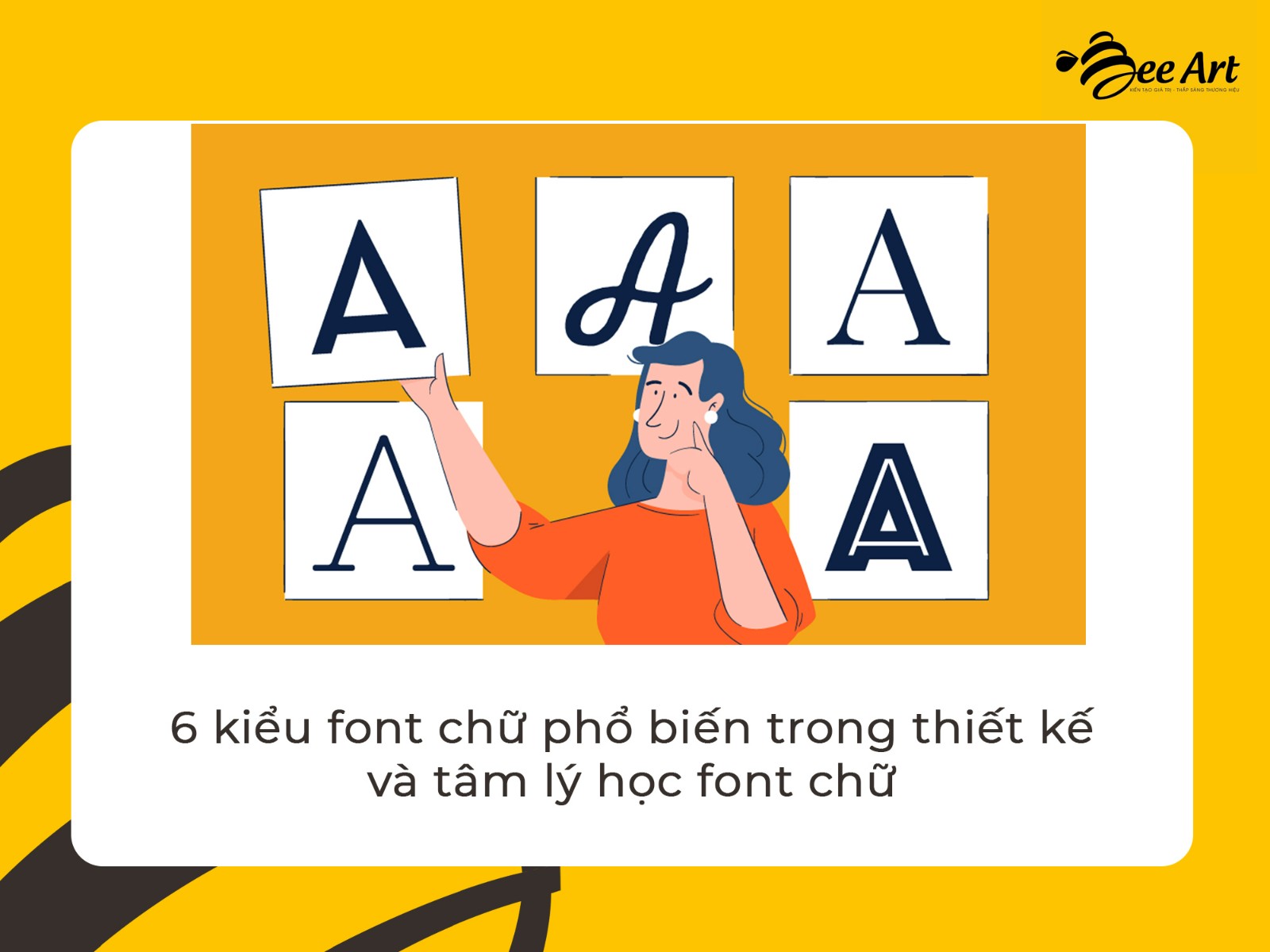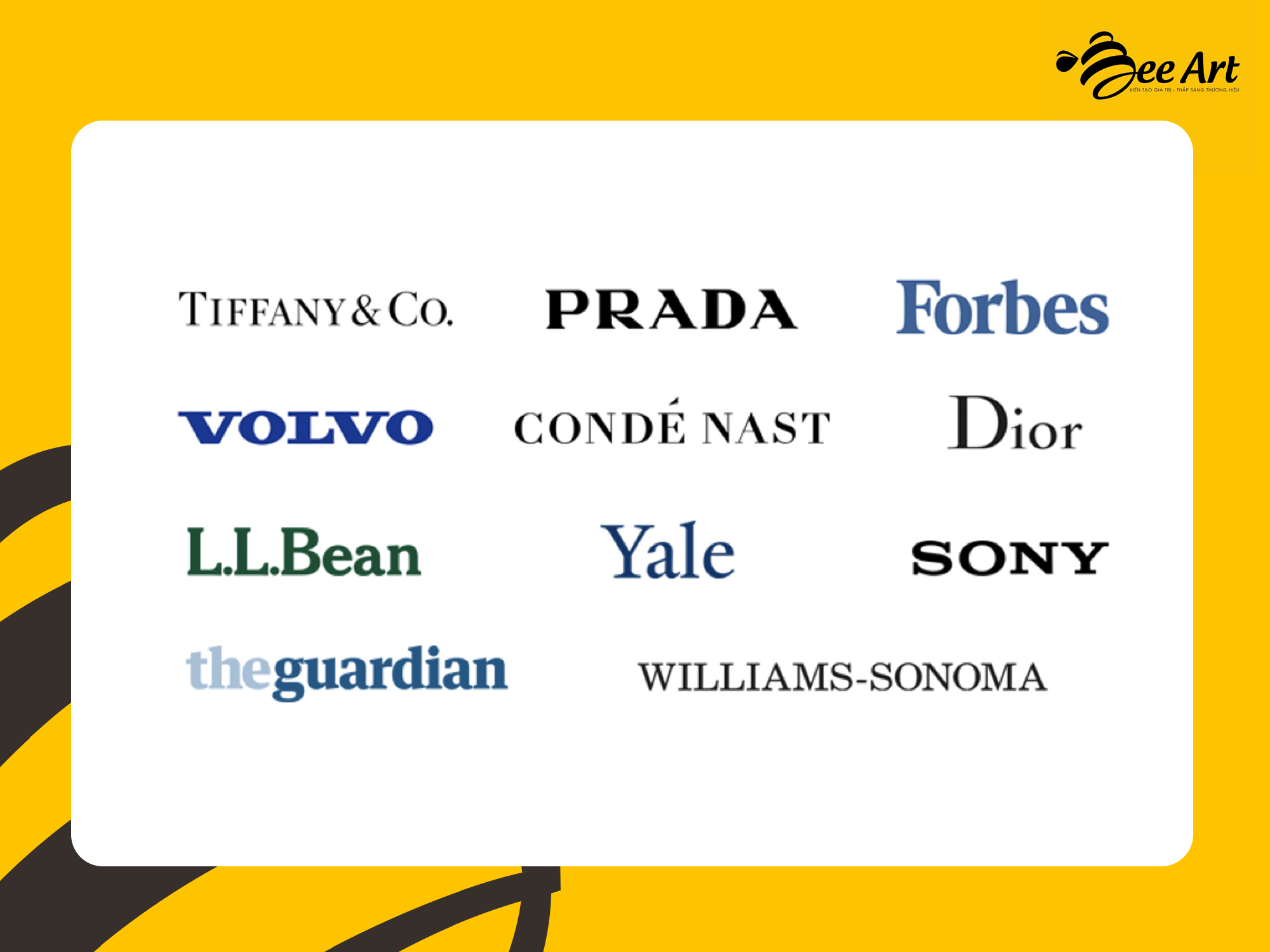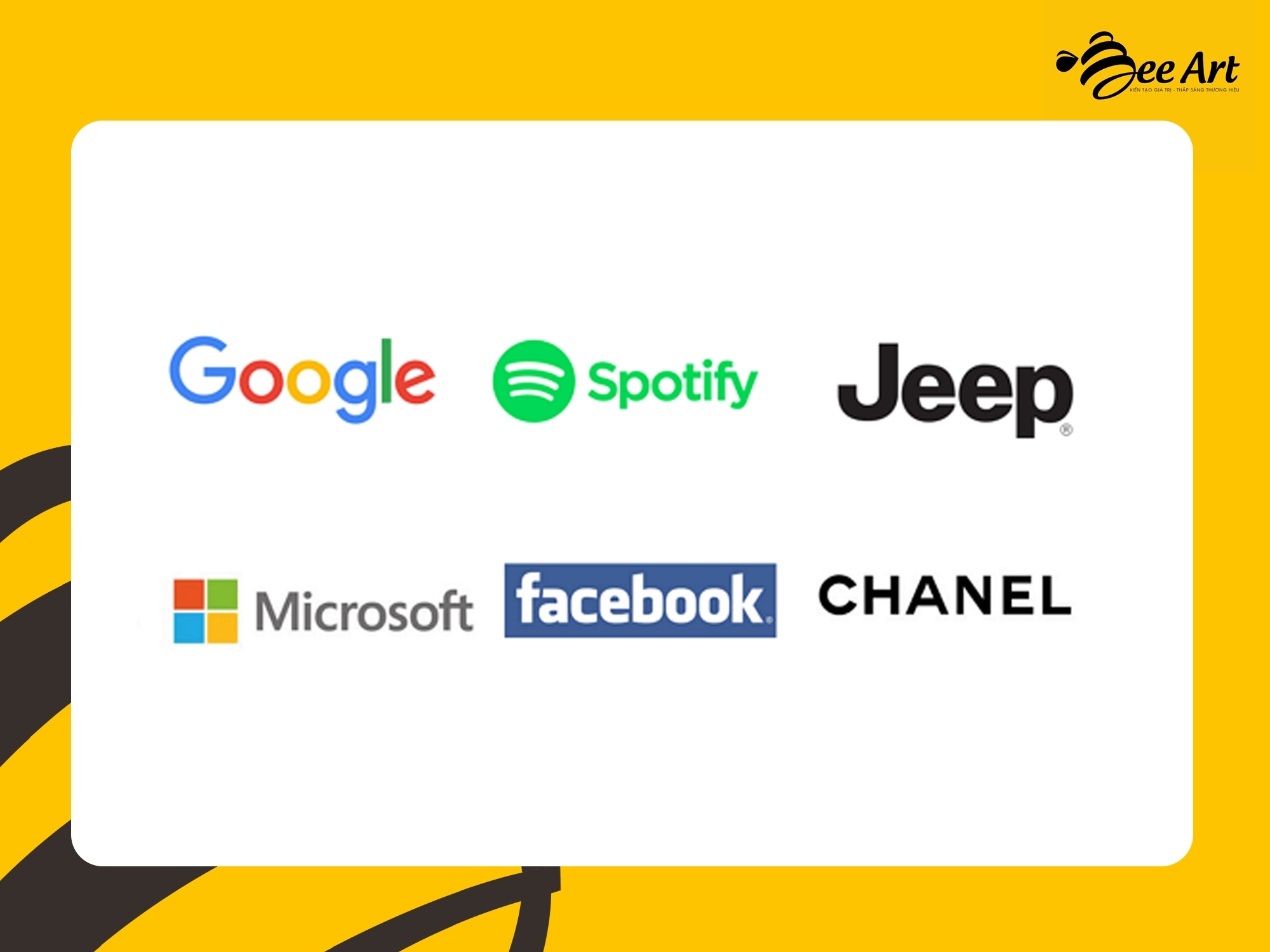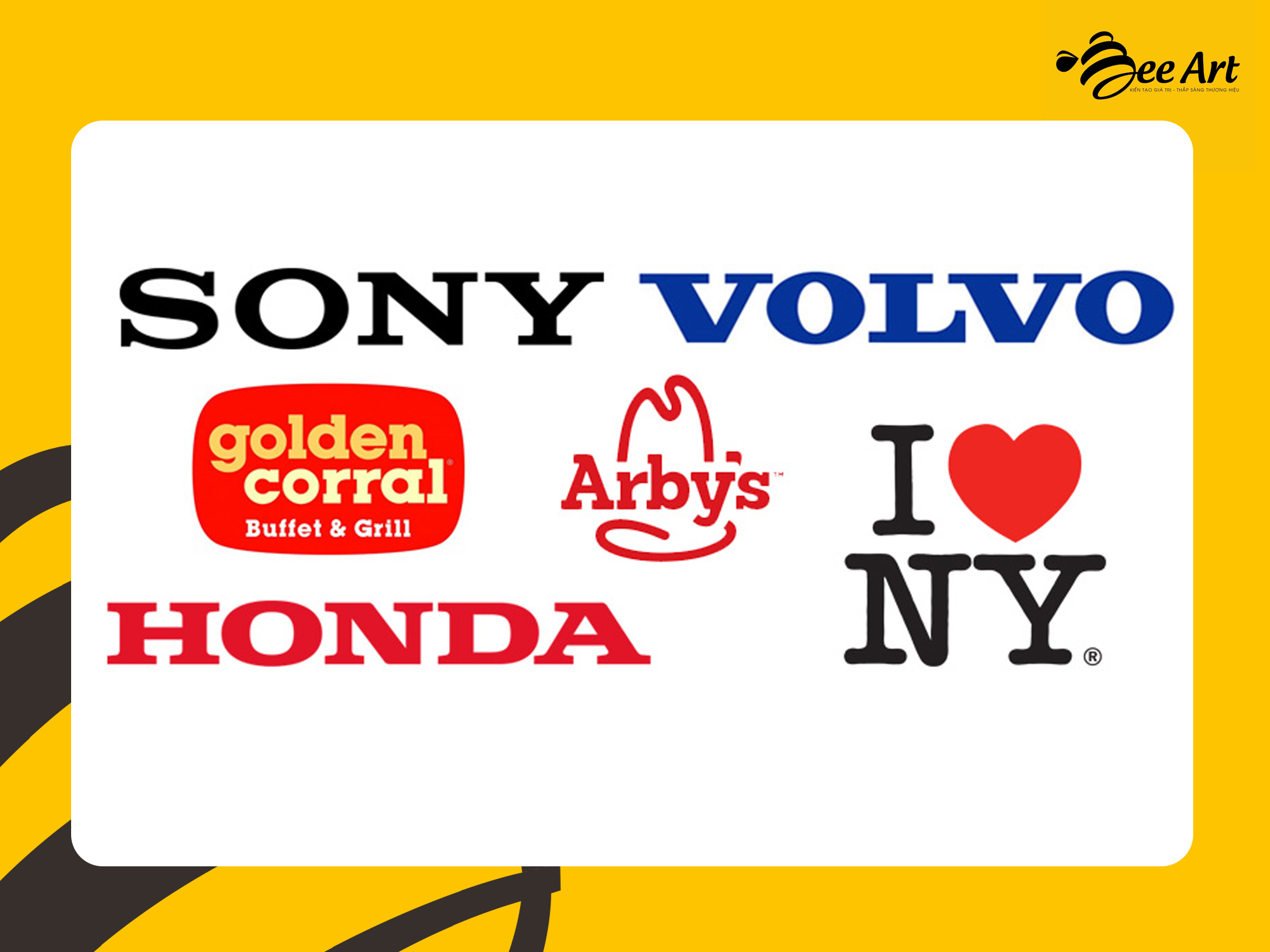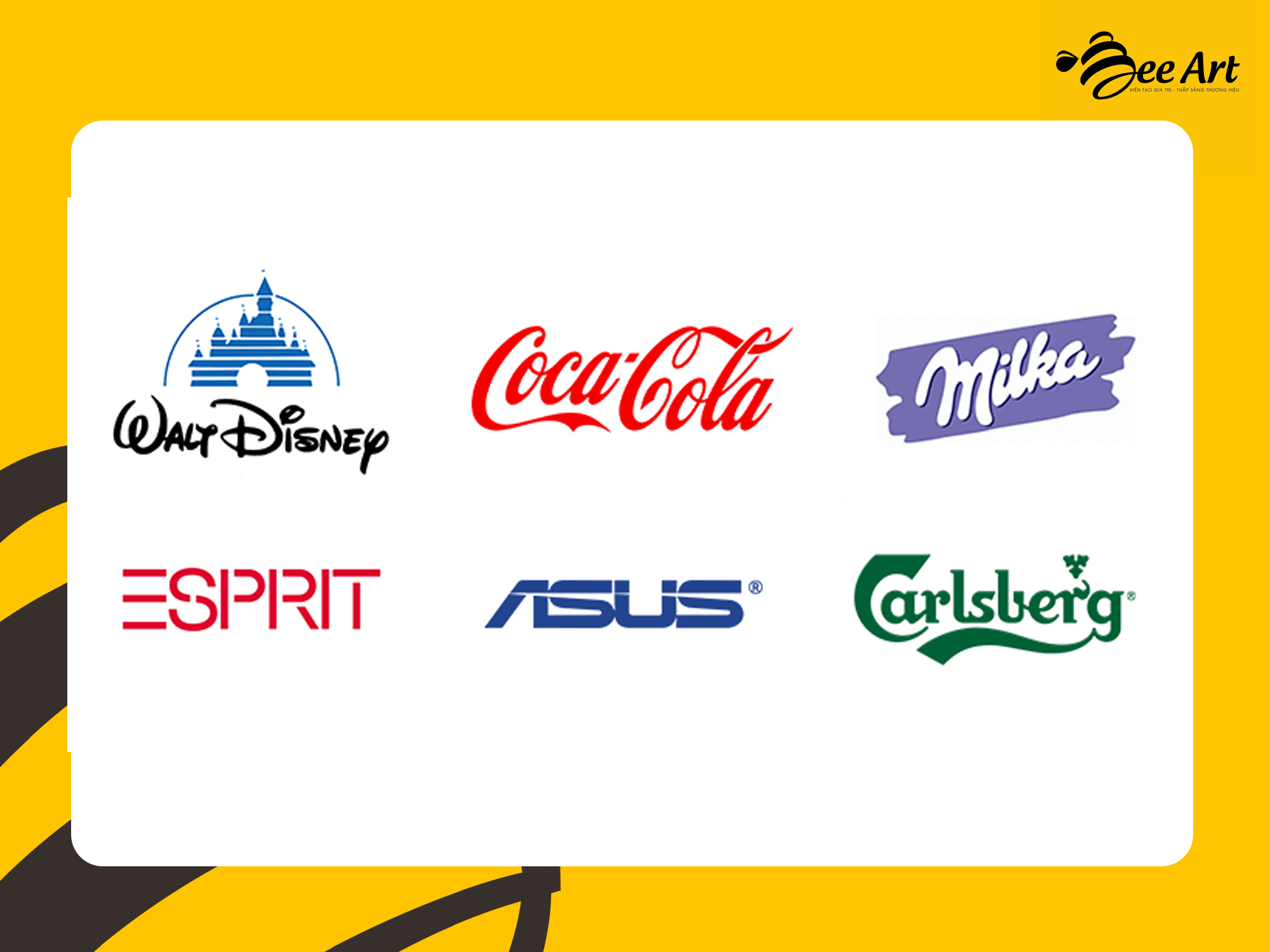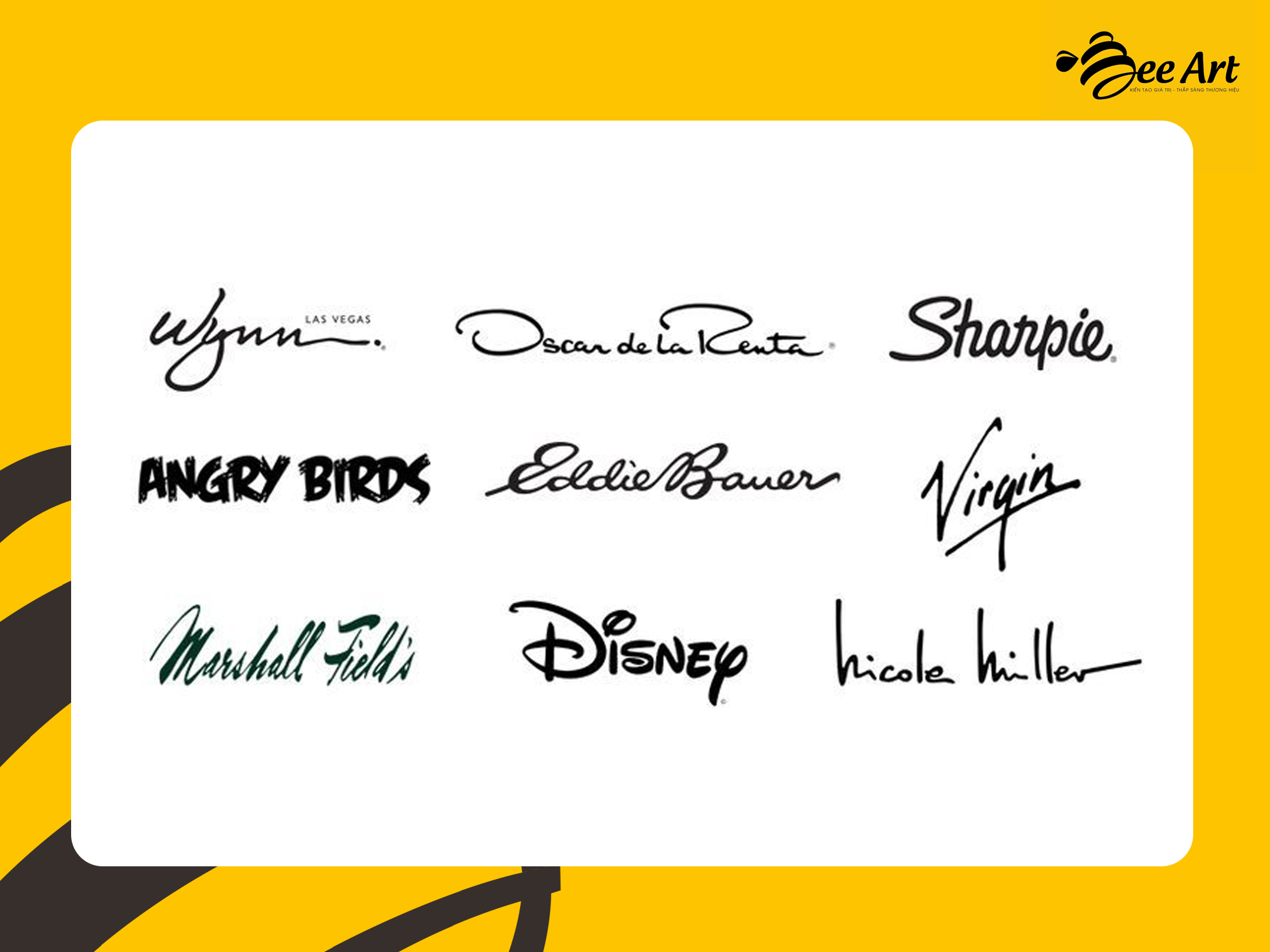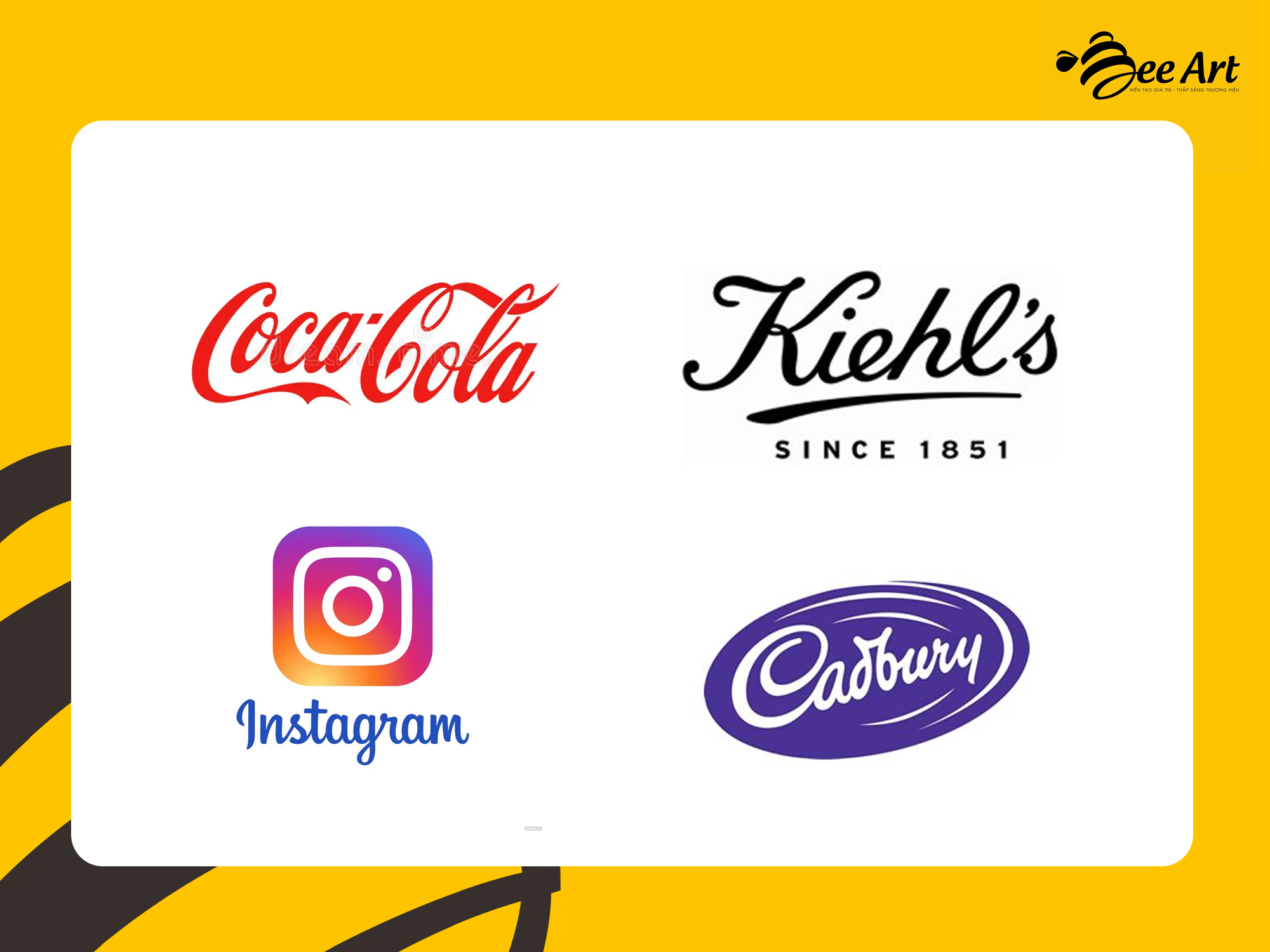
6 kiểu font chữ phổ biến trong thiết kế và tâm lý học font chữ
Font chữ là một thành phần quan trọng trong thương hiệu, có tác động rất lớn đến "cảm xúc"  của khách hàng. Hãy cùng Bee Art tìm hiểu về 6 kiểu font chữ phổ biến trong thiết kế  và tâm lý học font chữ.
Các kiểu font chữ phổ biến trong thiết kế  và tâm lý học font chữ
Trong thế giới ngày nay, nơi mà thông tin được truyền đạt qua nhiều phương tiện truyền thông khác nhau, việc chọn lựa font chữ phù hợp đã trở thành một yếu tố quan trọng không thể bỏ qua trong thiết kế đồ hoạ. Font chữ không chỉ đơn thuần là các ký tự để truyền tải văn bản, mà còn là một công cụ mạnh mẽ để truyền đạt cảm xúc, tạo ra ấn tượng và thiết lập sự nhận biết thương hiệu.
Font chữ có khả năng truyền đạt thông điệp. Mỗi font chữ mang đậm một cái phong cách riêng, từ sự truyền thống, chính thống đến sự hiện đại, cá nhân. Sự lựa chọn font chữ phù hợp không chỉ giúp văn bản trở nên dễ đọc mà còn giúp truyền tải một thông điệp cụ thể. Ví dụ, sử dụng font chữ chuyên nghiệp và trang trọng có thể phù hợp với một bản báo cáo kinh doanh, trong khi một font chữ vui nhộn và phóng khoáng sẽ là lựa chọn thích hợp cho một thẻ mời tiệc.
Ngoài ra, font chữ cũng đóng vai trò quan trọng trong việc xây dựng và củng cố nhận biết thương hiệu. Khi một font chữ được sử dụng liên tục trong các tài liệu, quảng cáo và trên các sản phẩm của một thương hiệu, nó tạo ra một hình ảnh nhận biết dễ nhận ra cho thương hiệu đó. Ví dụ, font chữ của Coca-Cola hay Nike đã trở thành biểu tượng của thương hiệu và không cần thêm bất kỳ logo nào khác để người tiêu dùng nhận biết.
Đồng thời, font chữ cũng góp phần vào việc tạo ra không gian và cảm xúc cho thiết kế đồ hoạ. Sự lựa chọn của font chữ có thể làm nổi bật một cảm xúc nhất định, từ sự vui vẻ, thoải mái đến sự nghiêm túc, trang trọng. Ví dụ, một font chữ vui nhộn và phóng khoáng có thể làm cho độc giả cảm thấy vui vẻ và thân thiện, trong khi một font chữ nghiêm túc và cổ điển có thể tạo ra một cảm giác nghiêm trang và uy nghiêm.
Các kiểu font chữ phổ biến trong thiết kế đồ hoạ
Trước khi đi sâu vào nội dung bài viết, cần phân biệt hai khái niệm rất dễ gây nhầm lẫn, mặc dù chúng rất khác nhau, đó là: Typeface và Font.
• Typeface hay Font Family là một tổ hợp những font chữ có cùng điểm chung trong thiết kế, không chịu giới hạn về kích thước cũng như định dạng (Ví dụ: Arial là một kiểu Typeface)
• Font thuộc Typeface và là biến thể của Typeface với định dạng xác định (Arial Regular, Arial Bold, hay Arial Italic...)
Về cơ bản, trong thiết kế đồ hoạ có 7 kiểu typeface. Mỗi typeface cũng có một tính cách riêng, một ý nghĩa riêng. Vì vậy, hiểu được thông điệp mà mỗi typeface truyền tải sẽ giúp quá trình lựa chọn kiểu chữ trở nên dễ dàng hơn.
1. Kiểu font chữ Serif
Font chữ Serif
Serif là kiểu chữ có chân, là một đường thẳng hoặc một nét nhỏ trong thành phần của chữ. Serif truyền tải cảm giác truyền thống, cổ điển, sự tin tưởng và sang trọng. Font này phù hợp với các thương hiệu lâu đời, uy quyền và cao cấp trong một số ngành như thời trang, tài chính, bảo hiểm: Rolex, Tiffany & Co, Gucci, Generali…
2. Kiểu font chữ Sans Serif
Font chữ Sans Serif
Ngược lại với Serif, San Serif là kiểu chữ không chân với các cạnh mượt mà, gọn gàng. Kiểu chữ này mang đến cảm giác hiện đại, đơn giản, rõ ràng và thân thiện hơn. Loại font này thường được các thương hiệu về công nghệ, startup trẻ trung, sáng tạo lựa chọn: Microsoft, Panasonic, Facebook…
3. Kiểu font chữ Slab Serif
Font chữ Slab Serif
Là một biến thể của Serif, nhưng Slab Serif to và đậm hơn mang tới cảm giác mạnh mẽ, tự tin và nam tính. Các thương hiệu bia và xe hơi có xu hướng sử dụng kiểu chữ này: Heineken, Honda, Volvo… và ngay cả Rubyk cũng đang sử dụng kiểu chữ này.
4. Kiểu font chữ Decorative
Font chữ Decorative
Font chữ Decorative là một kiểu font đặc biệt được thiết kế để thu hút sự chú ý và tạo ra sự ấn tượng mạnh mẽ. Đặc điểm chung của các font Decorative là chúng thường có những đặc tính độc đáo và phong phú, thường kết hợp các yếu tố hình ảnh, hoa văn, hoặc các trang trí phức tạp khác. Decorative phù hợp với các thương hiệu muốn thể hiện cá tính thương hiệu riêng và kết nối cảm xúc với đối tượng mục tiêu. Các thương hiệu như Fanta, LEGO, Disney, McDonald's và nhiều thương hiệu khác đã áp dụng typeface này.
5. Kiểu font chữ Handwritten
Font chữ Handwritten
Handwritten là kiểu chữ viết tay, mang tính cá nhân, mang đến cảm giác thân thiện, gần gũi và vui tươi hơn các font chữ khác. Các thương hiệu như Barbie, Kellogg's, Harrods... đang sử dụng kiểu chữ này.
6. Kiểu font chữ Script
Font chữ Script
Script là một kiểu font chữ viết tay, Script gợi lên cảm giác thanh lịch, duyên dáng, gần gũi nhưng không kém phần khác biệt. Kiểu chữ này thích hợp với các thương hiệu liên quan đến mỹ phẩm, thời trang và nghệ thuật... Một số thương hiệu sử dụng kiểu chữ này có thể kể đến: Kiehl's, Coca-Cola, Instagram, Cadbury.